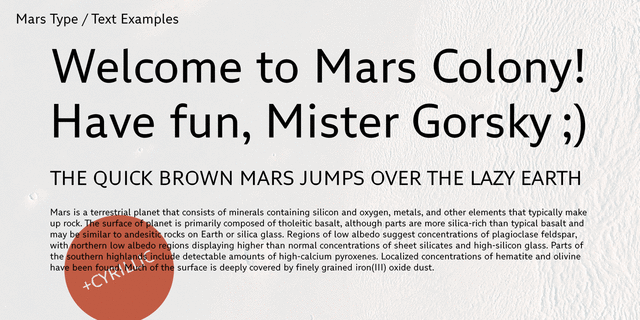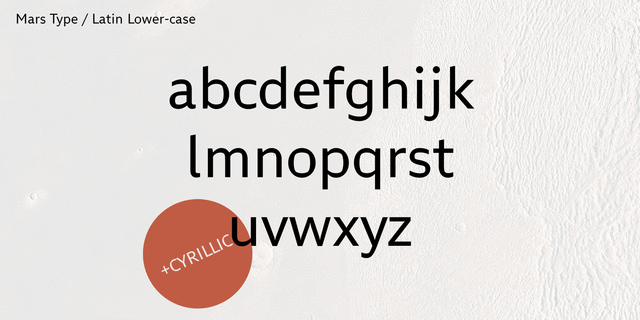
Mars Type – это гротеск с открытыми формами и другими чертами, повышающими его распознаваемость и удобочитаемость. Идеально подходит для навигации и интерфейсов в марсианской колонии. Главной фишкой шрифта является особая форма овальных символов (идеальный круг снаружи, «иллюминатор» внутри) и соответствие угла наклона некоторых знаков (например, слеш) углу наклона оси вращения Марса – 25,19°. Вертикальные срезы открытых знаков, как в шрифтах Futura или Gill Sans, позволяют новому шрифту иметь высокую емкость, как у гуманистических гротесков, но сохранять видимую геометричность. Шрифт Mars Type разработан Евгением Садко в 2018-2019 году и выпущен компанией Rentafont по бесплатной лицензии SIL Open Font License (OFL).
Ассоциации c семейством Mars TypeКачества и характер:
городской, современный, лаконичный, точный, строгий, ясный, ровный, понятный, качественный, простой, серьезный, спокойный, четкий, резкий, твердый, глобализированный, умный, глобалистичный, инженерный, чертежный, космический, убедительный, практичный, прагматичный, техничный, урбанистичный, логичный, гладкий, комфортный, удобный